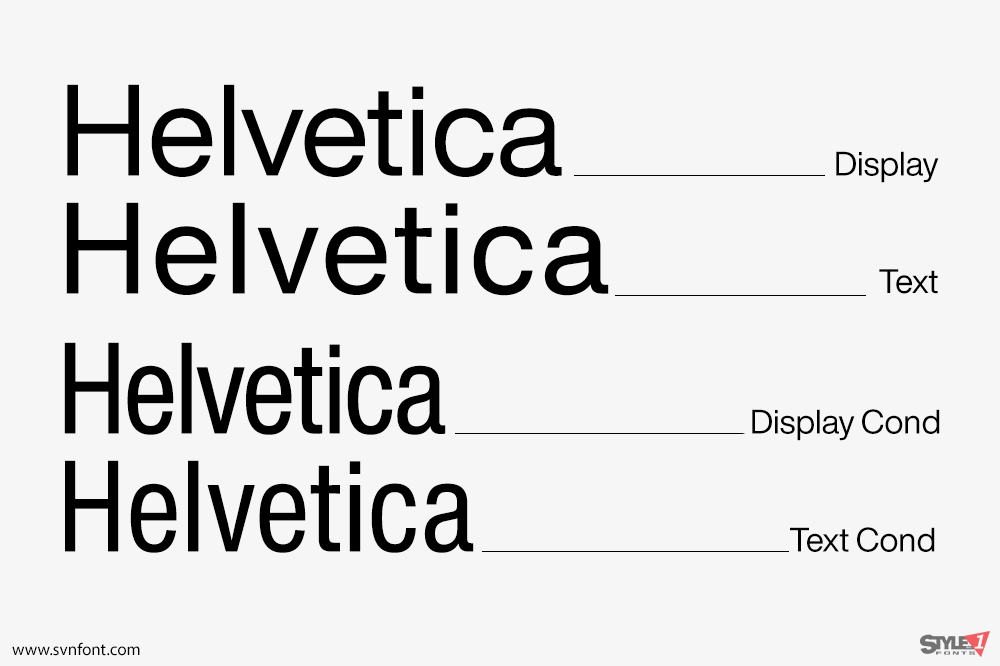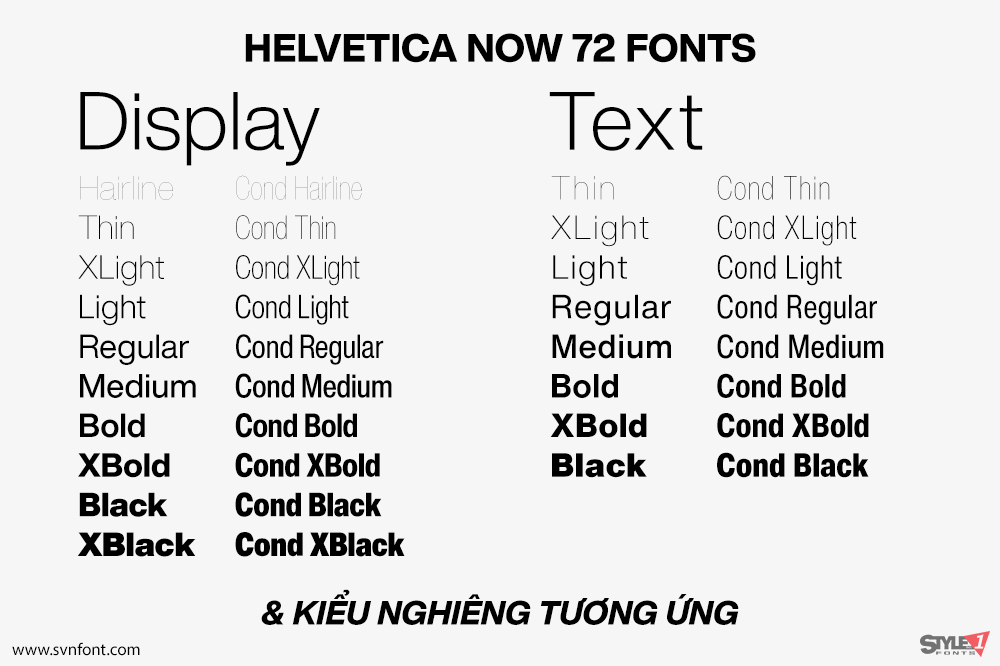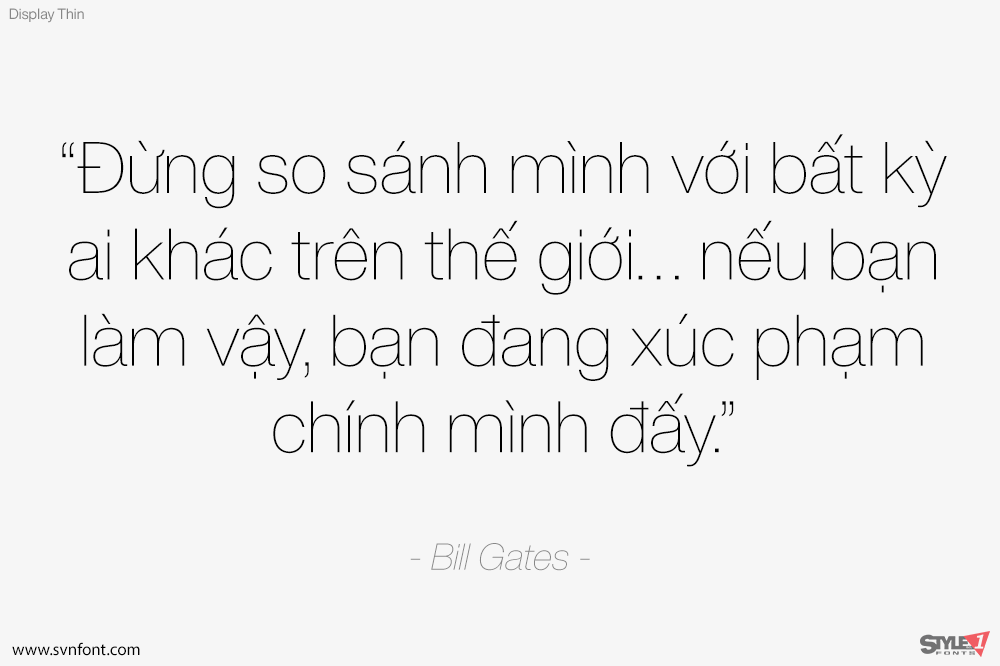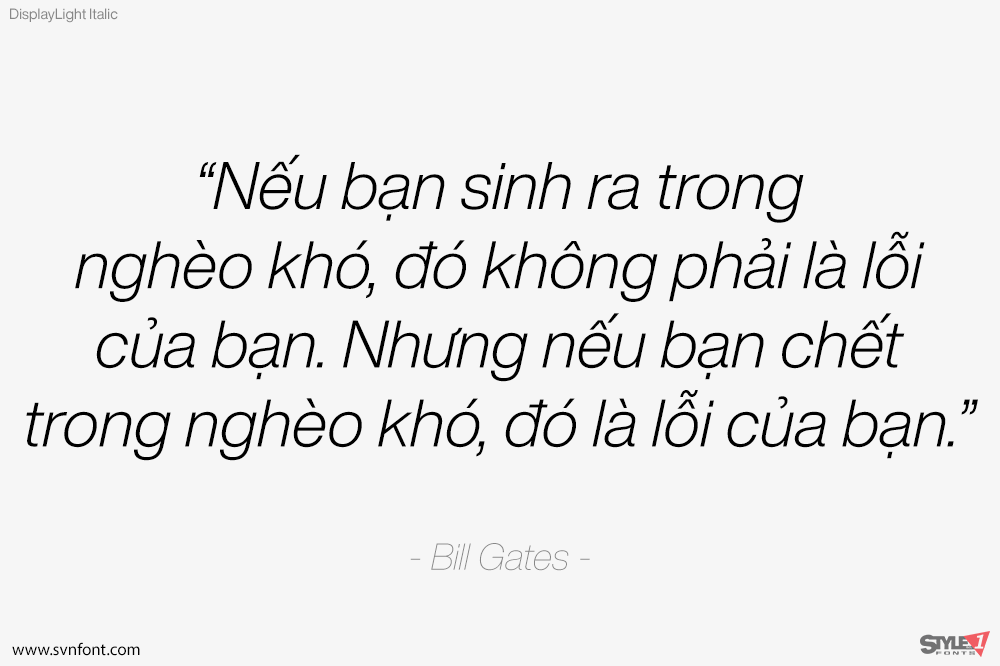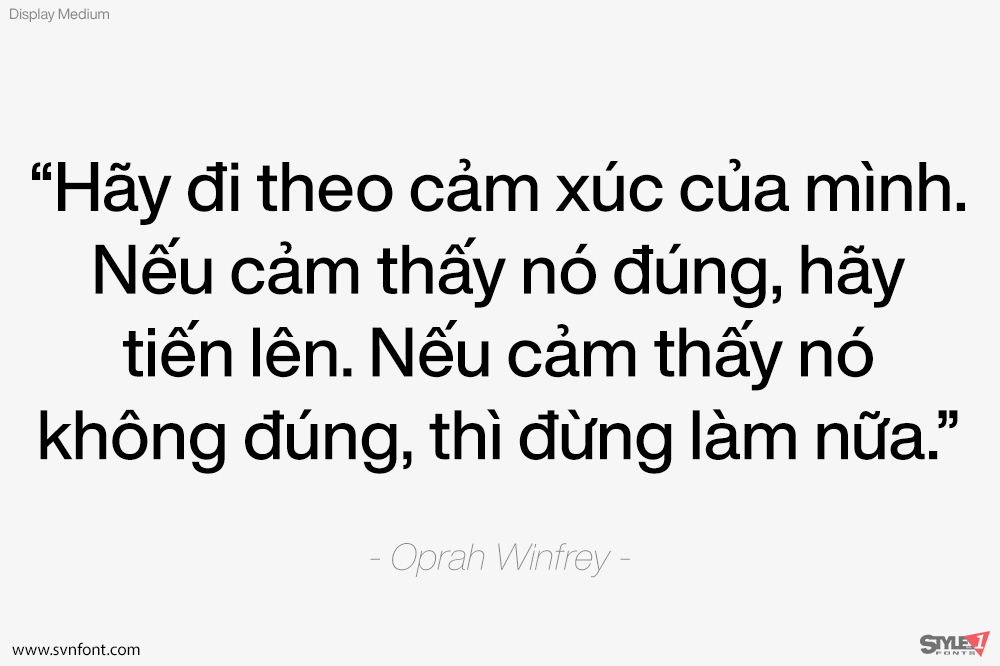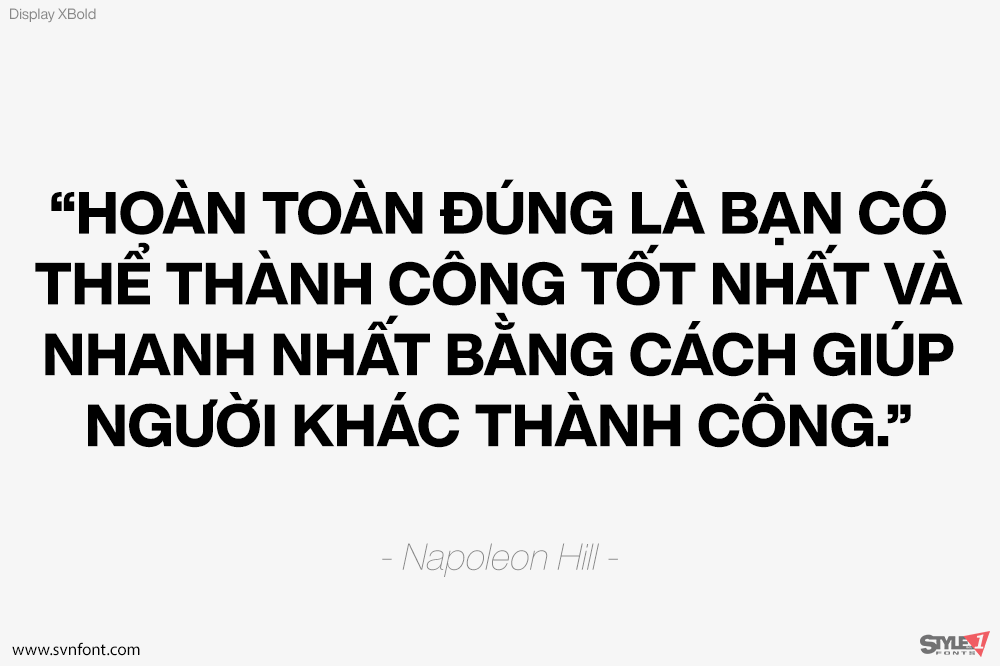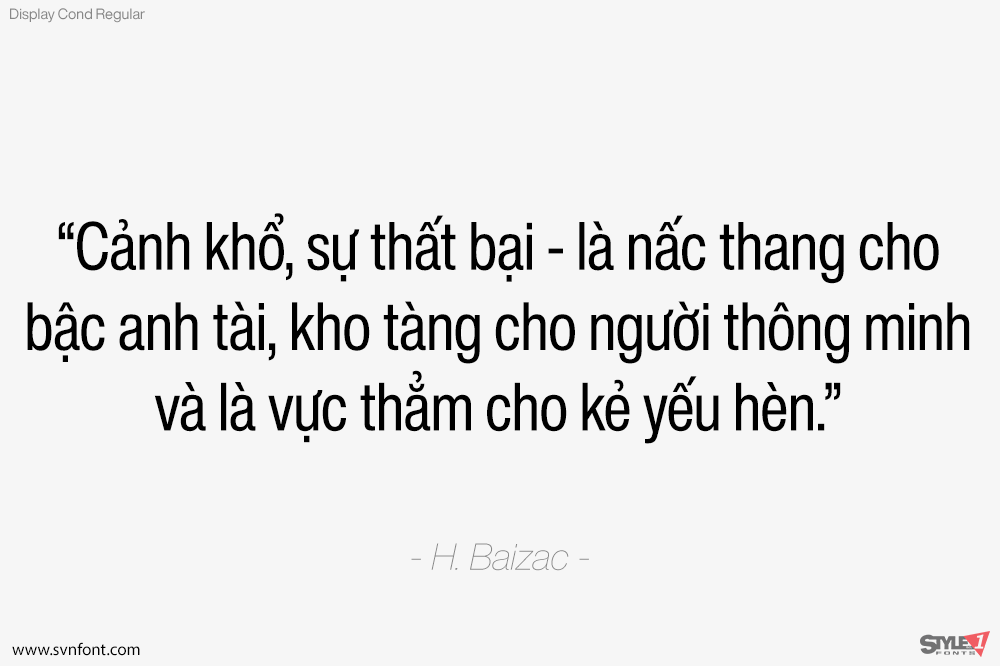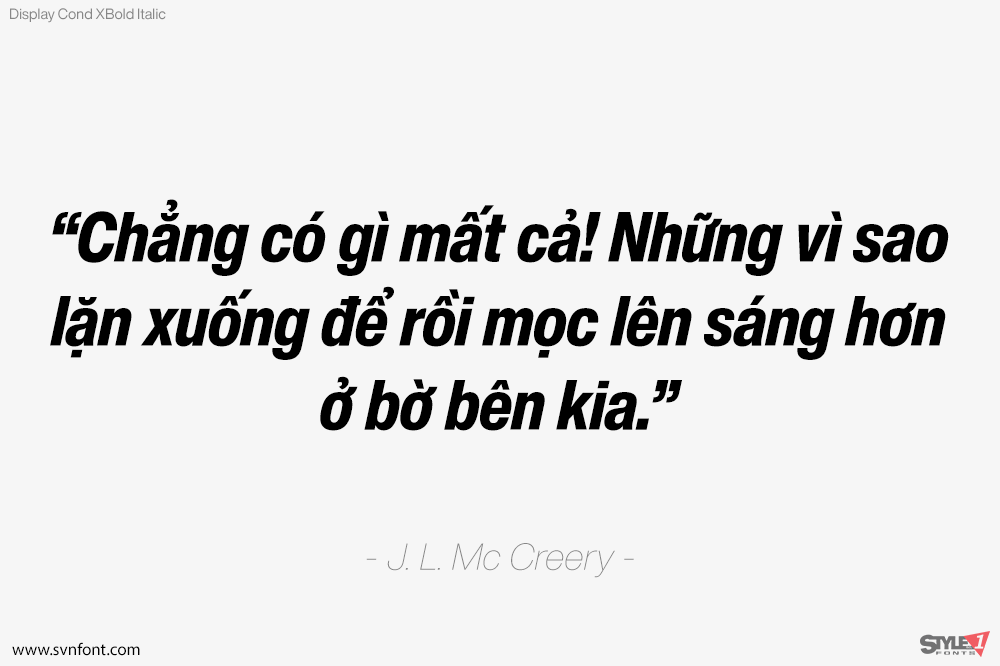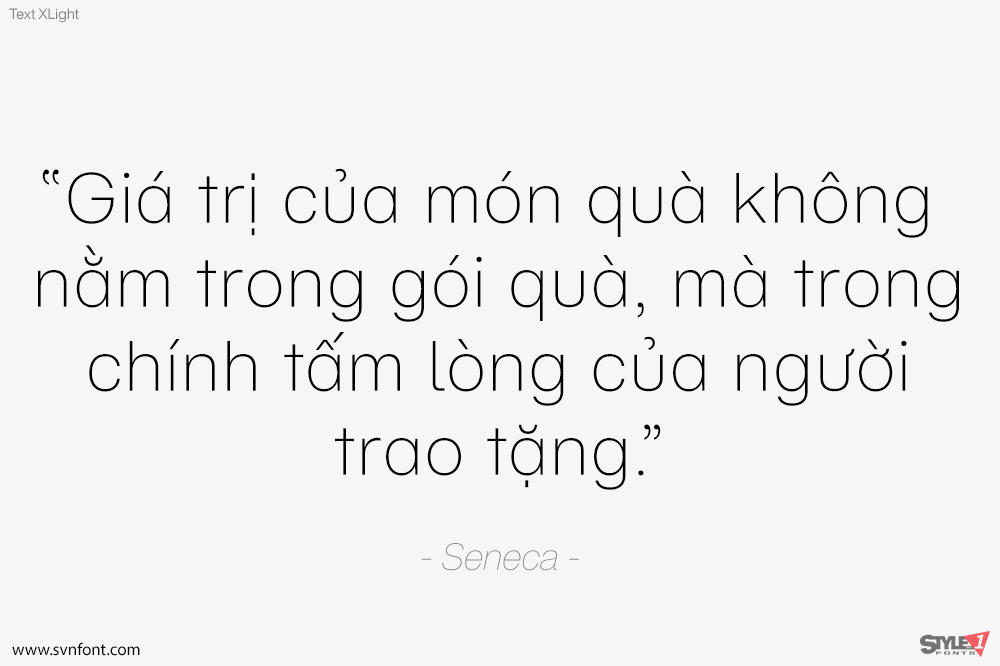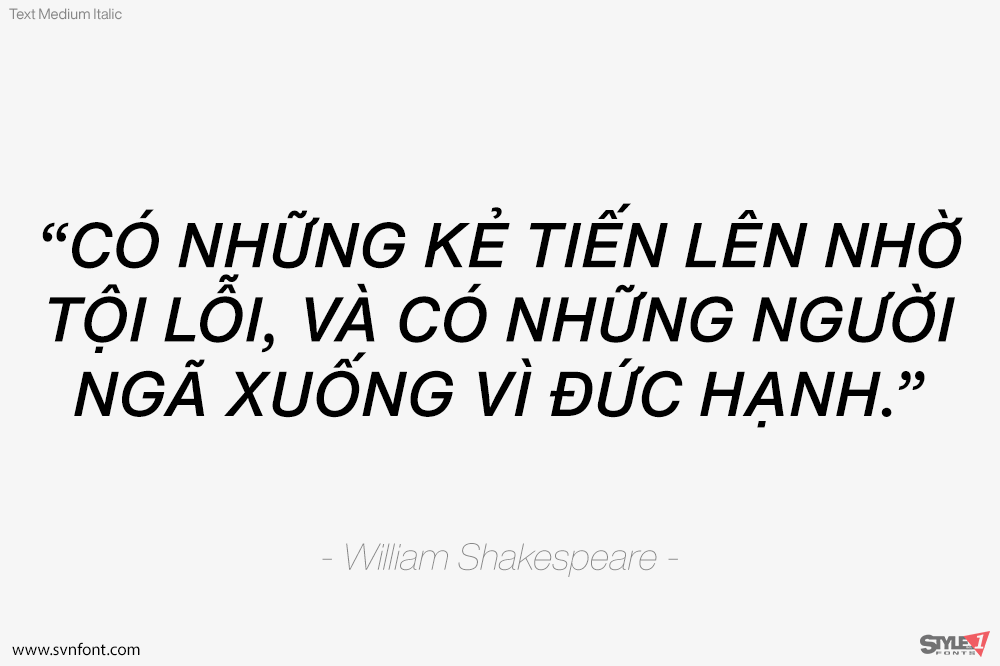
Helvetica® Now là một chương mới trong câu chuyện về kiểu chữ có lẽ nổi tiếng nhất mọi thời đại. Có sẵn ba kích thước quang học—Micro, Text, và Display—mỗi ký tự trong Helvetica Now đều đã được vẽ lại và điều chỉnh, cùng với việc bổ sung nhiều ký tự thay thế hữu ích. Phông chữ này có mọi thứ chúng ta yêu thích ở Helvetica và mọi thứ chúng ta cần cho ngành in ấn ngày nay.
Đây không phải là một sự hồi sinh. Đây không phải là một sự phục hồi.
Đây là một tuyên ngôn.
Đây là Helvetica Now: dành cho mọi người, ở mọi nơi, cho mọi thứ.
Nhà thiết kế: Charles Nix, Jan Hendrik Weber, Alexander Roth, Juan Villanueva, Terrance Weinzierl, Tom Rickner.
Nhà phát hành: Monotype